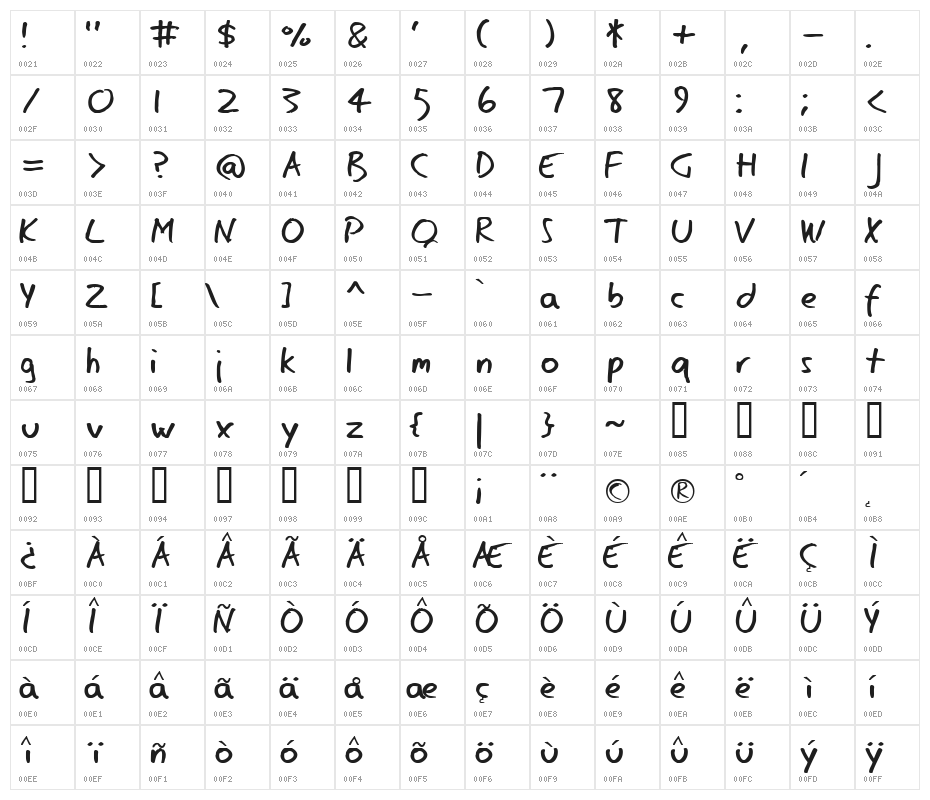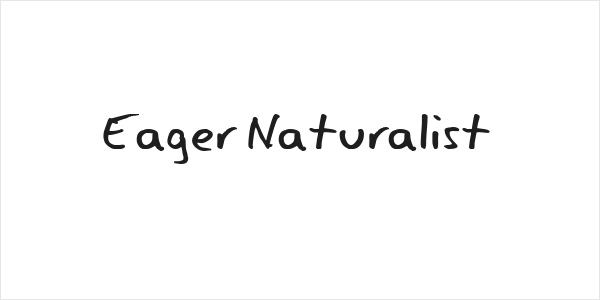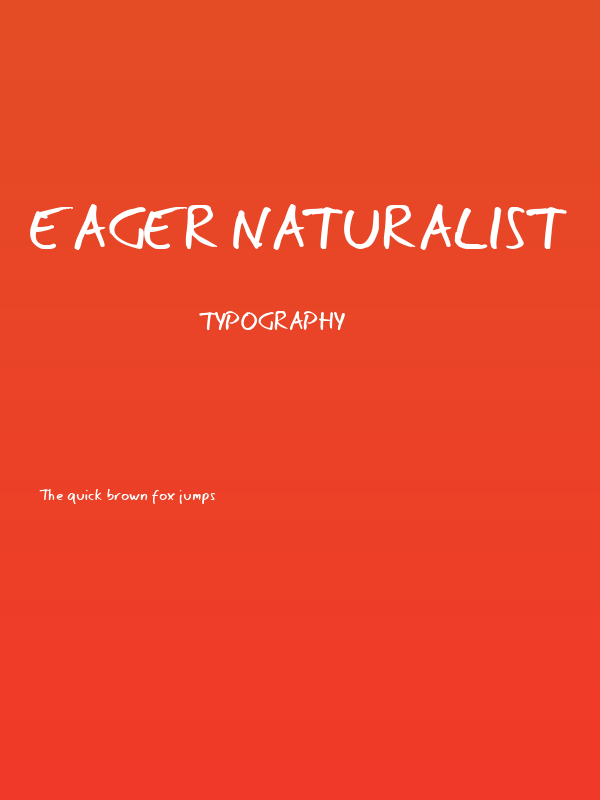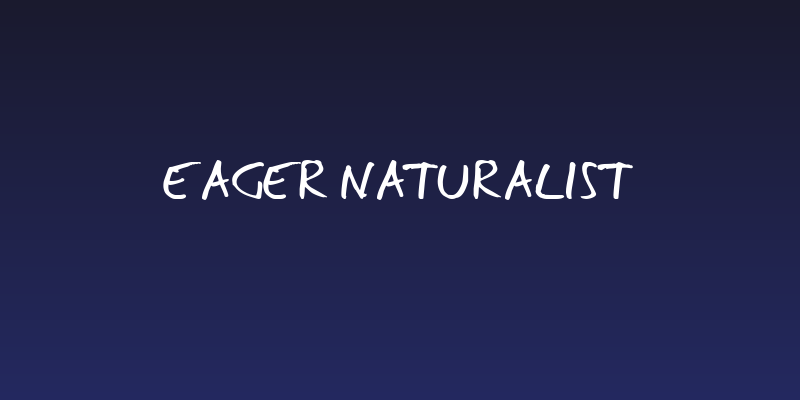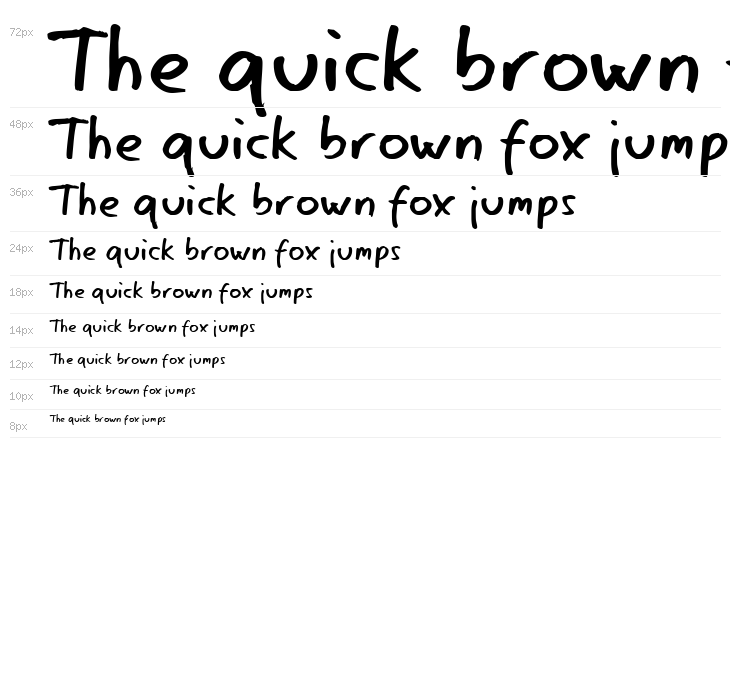
Eager Naturalist Font
| Estilo general | Casual |
| Caso de uso | Logos, Invitations, Greeting Cards |
| Proyectos propuestos | Ideal for projects that require a personal touch, such as greeting cards, invitations, or branding for creative businesses. |